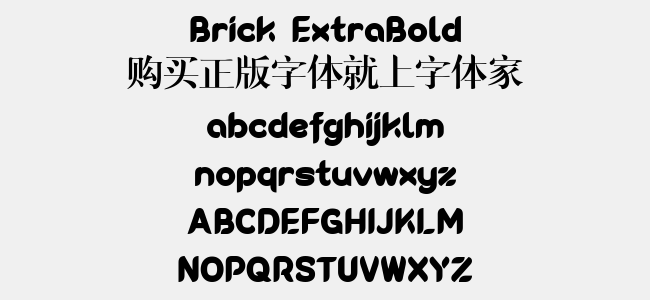
Brick ExtraBold
字体名称:Brick ExtraBold
字体字数:26个英文大小写字母及和阿拉伯数字
Brick ExtraBold
Brick ExtraBold是一款个性独特的英文字体,非常适合创意类的PS字体,英文广告设计载体上使用,在设计中选择这款字体应用的话,会起到非常理想的效果。此款字体适用于个人学习交流,字体研究以及一些非商业用途的载体中,由三极字库出品,字体家平台整理发布。